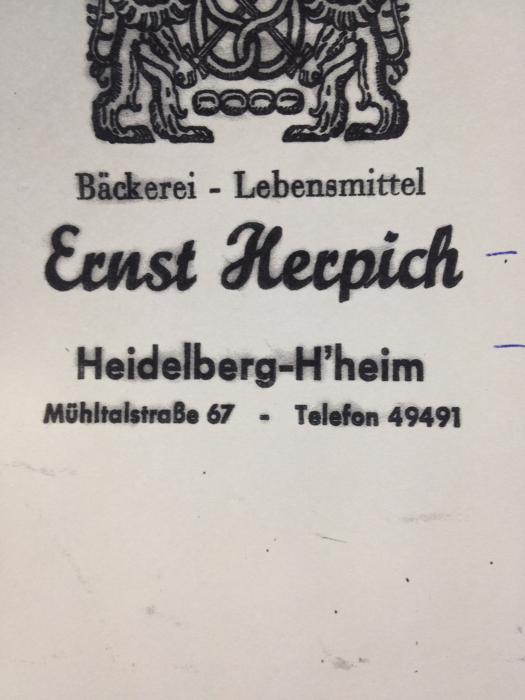
Schriftart Bäckertüte
ich soll die Schift "Ernst Herpich" und noch weitere 3 Namen als Grabinschrift einhauen. Hat jemand einen Tipp welche Font ich nehmen könnte?
Zu meinen Lebzeiten gab es die Bäckerei schon nicht mehr, deswegen vermute ich das die Tüte und somit die Schrift schon über 30 Jahre alt ist. Das kleine "r" gefällt mir nicht so recht weil es auch schwer zu meißeln ist, aber das große "E" ist perfekt.
Ich nehme deine Font als Vorlage und überzeichne sie noch einwenig.